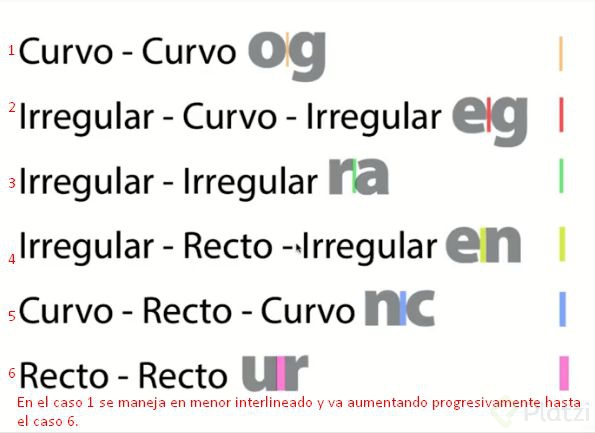
¿Cómo programar una tipografía funcional y legible?
El diseño tipográfico no solo implica estética, sino también funcionalidad y adaptabilidad en diversos contextos.
Aquí te guiamos a través de aspectos esenciales para lograrlo:
1. Interletrado y agrupación de letras
El interletrado define la separación entre caracteres para garantizar su legibilidad. Para un espaciado eficiente:
Agrupación por trazos verticales
- Ascendentes con trazo vertical a la izquierda: B, H, K, L.
- Trazos verticales a la izquierda: M, N, R, U.
- Excepciones: F y J, que necesitan ajustes específicos.
Agrupación por curvas y aperturas
- Curvas a la izquierda: C, E, O.
- Aperturas a la izquierda: S, con excepciones como la G.
Agrupación por diagonales y casos especiales
- Diagonales a la izquierda: Z, V.
- Trazos descendentes únicos: J.
Estas agrupaciones simplifican la asignación de valores de espaciado y mantienen consistencia.
Rúbrica para usar en los interletrados. Apuntes de la imagen por lalitacomics.
Glyphs facilita el trabajo con herramientas avanzadas para automatizar el espaciado:
Asignación manual y automatización
- Repite valores en letras similares para ahorrar tiempo.
- Usa
Ctrl + Alt + ←/→para ajustar manualmente el espaciado.
Ajuste fino
- Refina valores usando guías visuales y asegurándote de que las curvas y trazos no se superpongan.
El kerning corrige problemas de espaciado específicos que el interletrado no puede resolver. Es clave en pares con formas que generan espacios irregulares, como:
- Curva y angular: AV, WA, Ta.
- Curva y curva: OO, CO.
Automatización del kerning:
- Define grupos de kerning para pares similares y ajusta valores uniformemente.
- Usa el panel de kerning de Glyphs para administrar ajustes precisos.
SpeedPunk: Úsalo para evaluar la fluidez de las curvas.
Overshoots y guías de alineación:
- Ajusta las curvas para que se vean visualmente alineadas, incluso si geométricamente no lo están.
5. Referencias esenciales: Doyald Young
Un nombre relevante en tipografía es Doyald Young, un maestro del diseño de letras que enfatizaba la coherencia y elegancia en cada carácter.